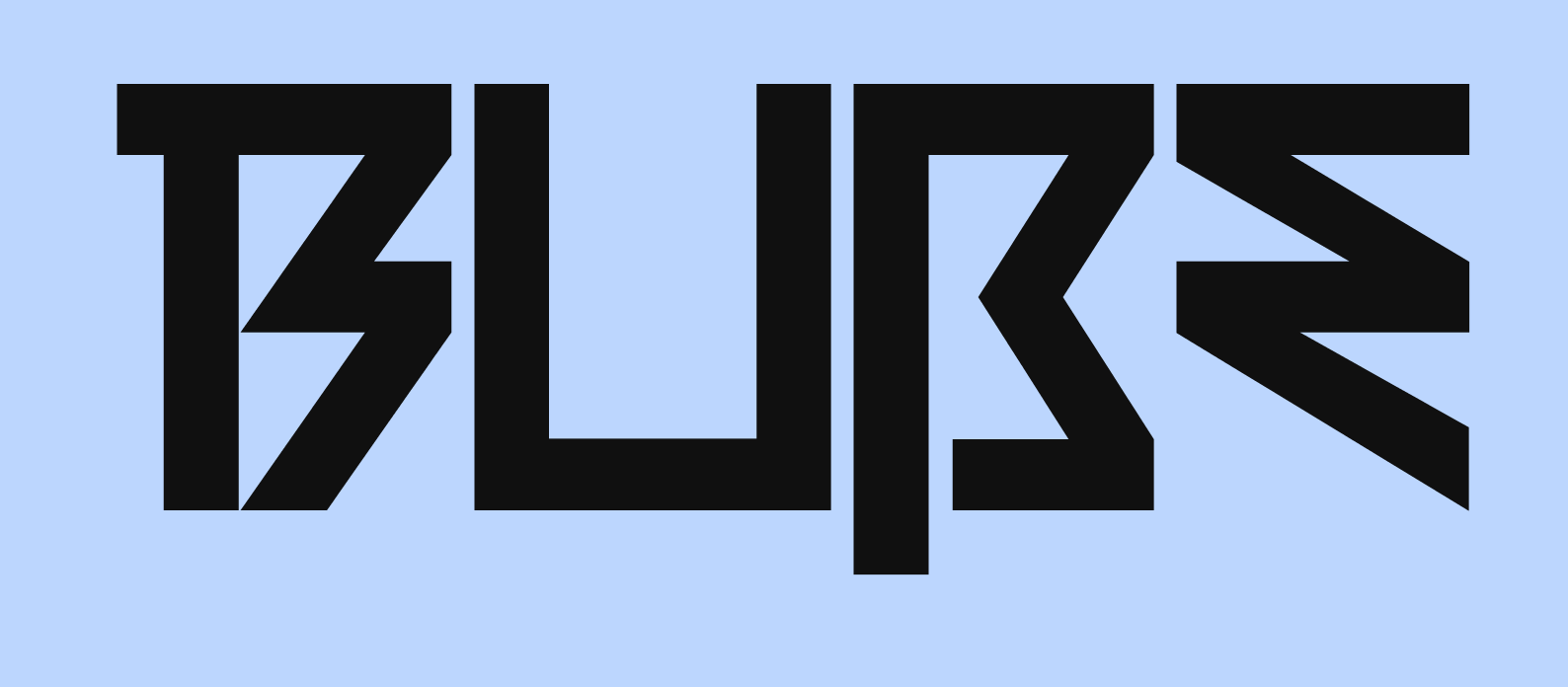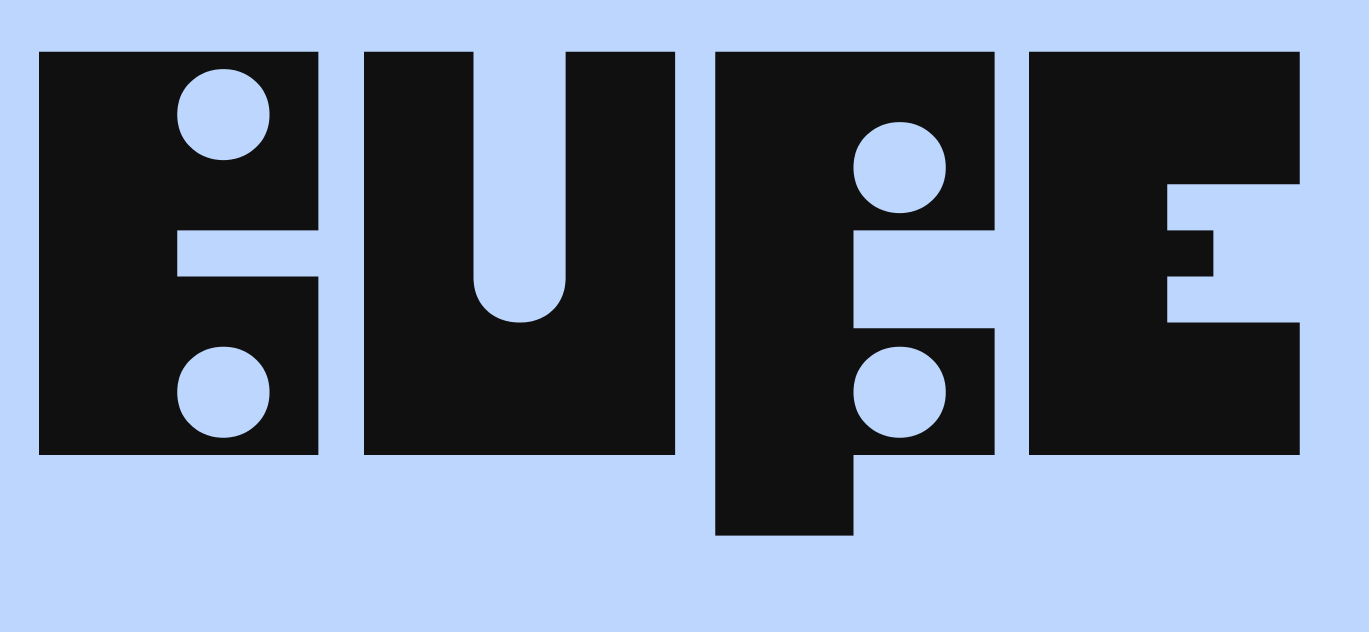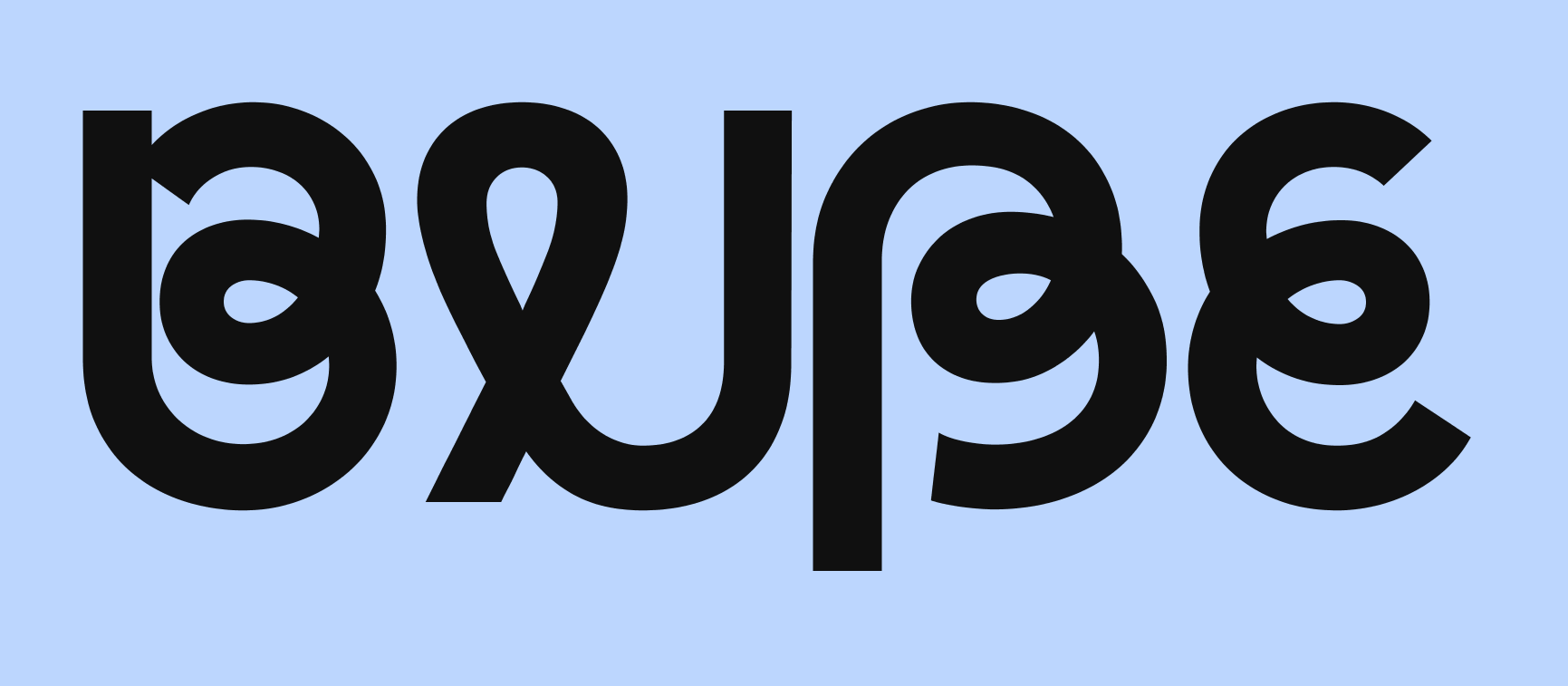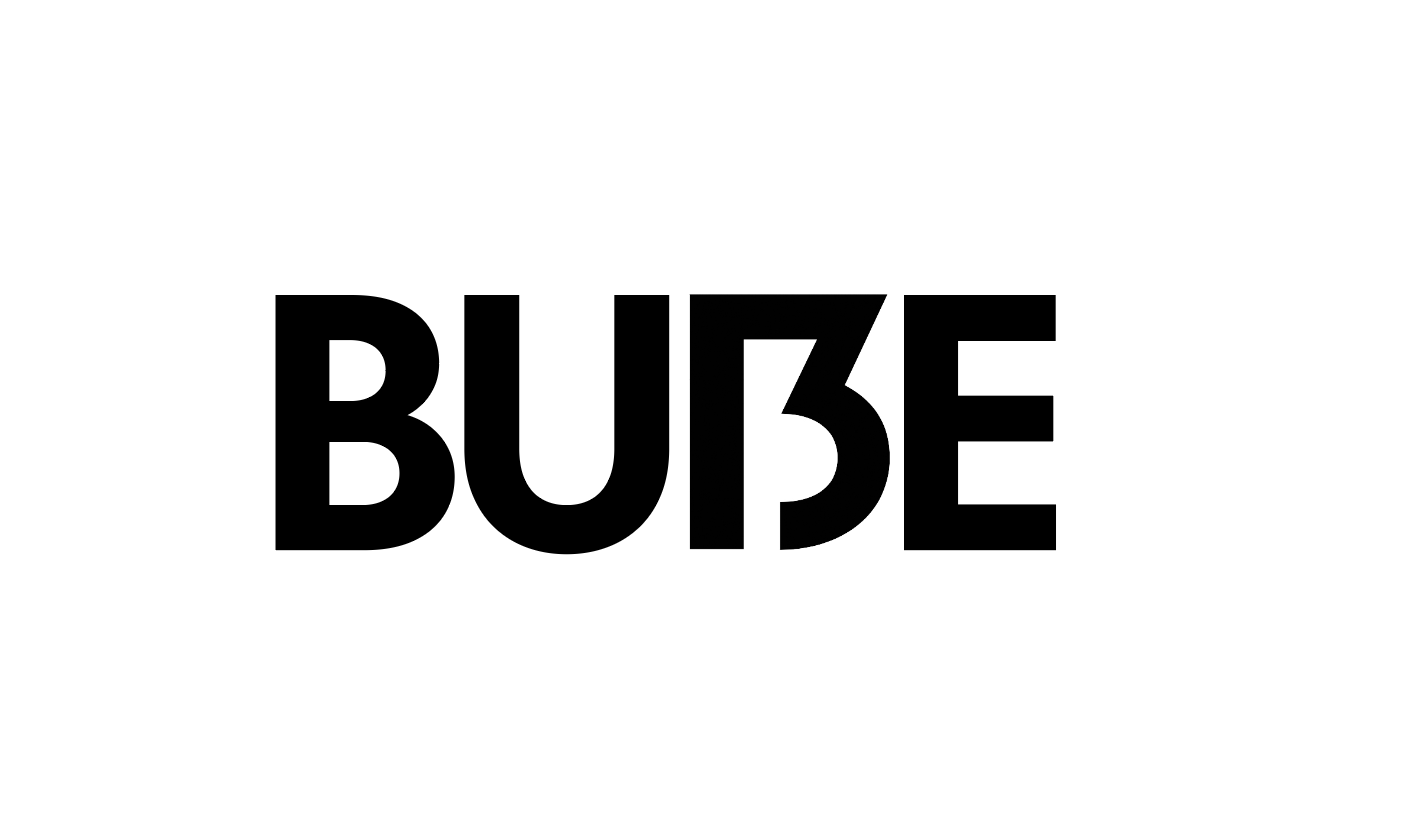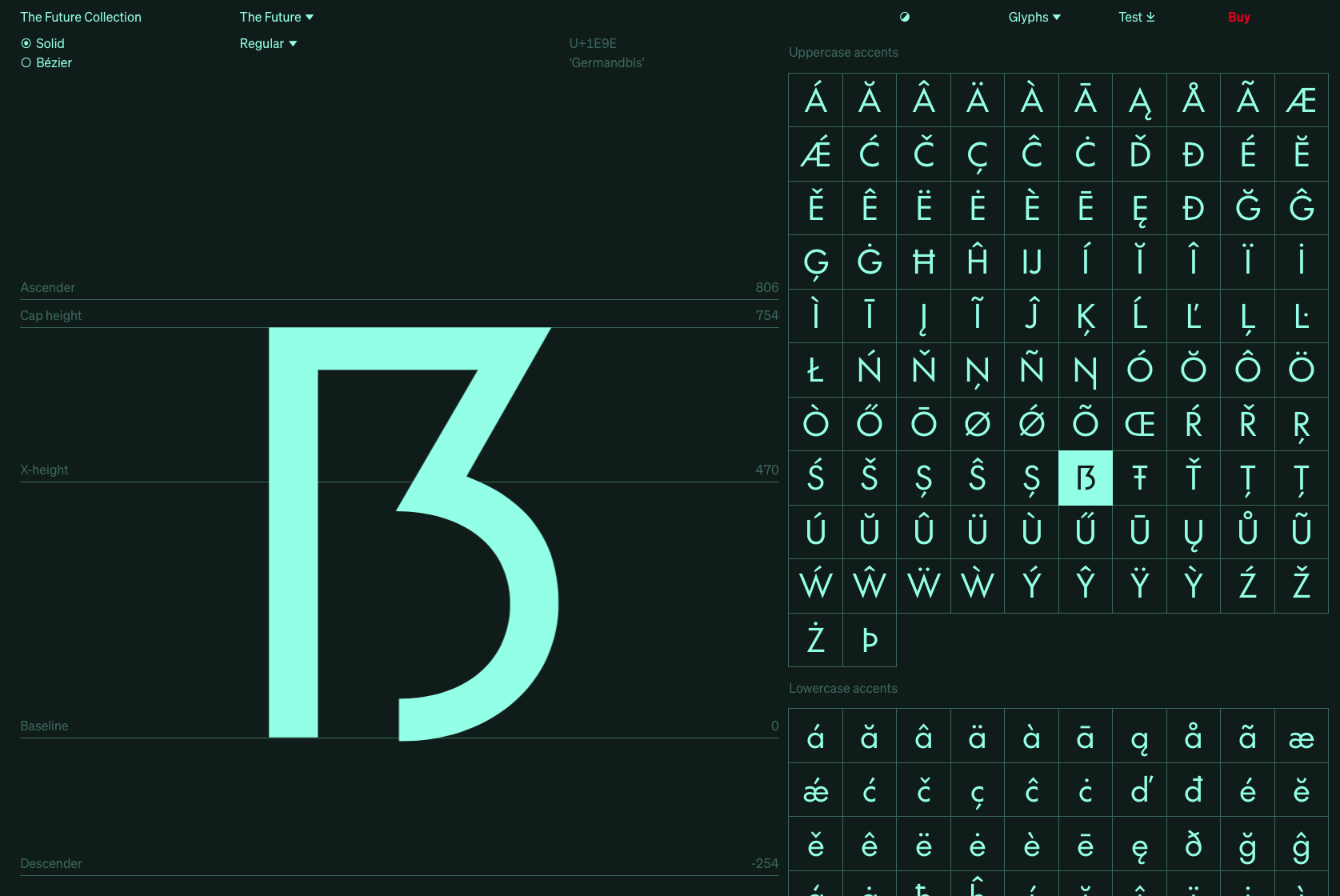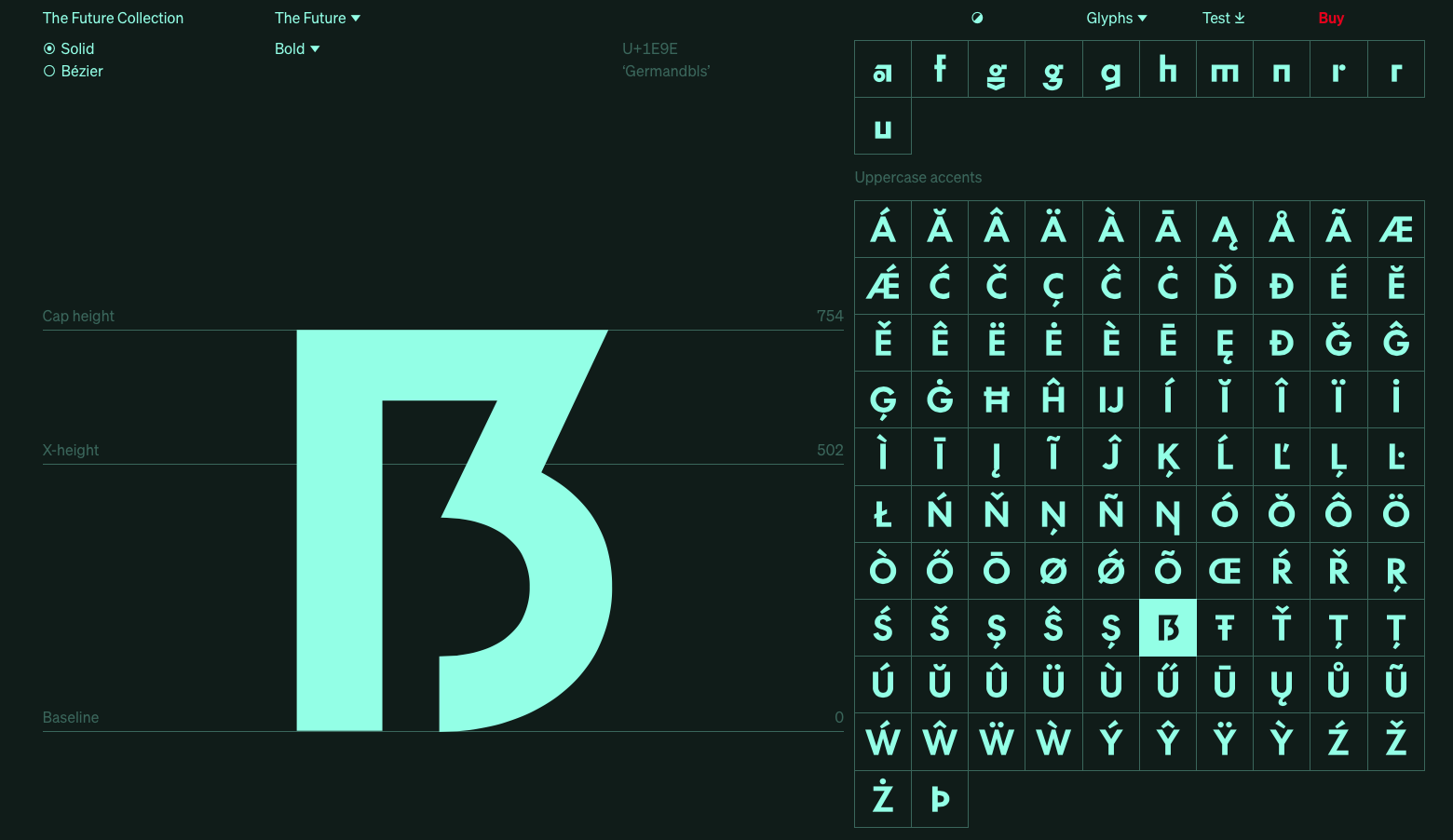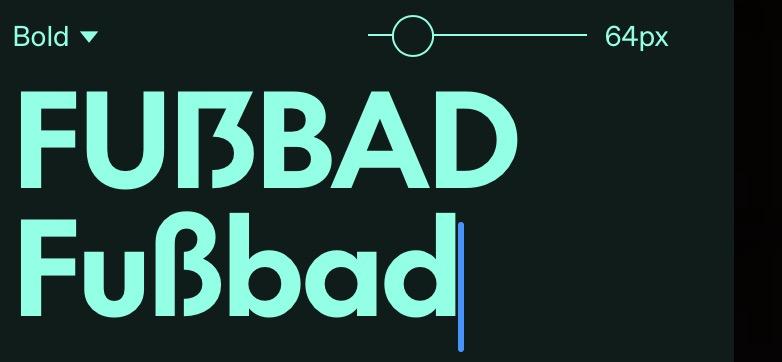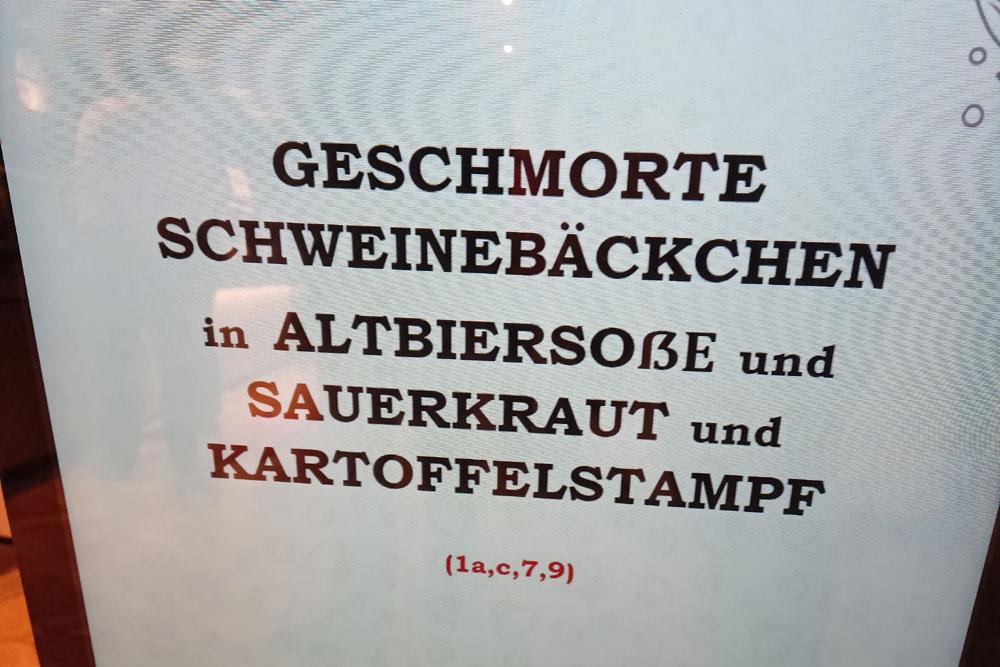
Wenn hier einer eine Einlegesohle braucht ist es die obere Innenform. Viel zu klein im Vergleich zur Unteren.
Aber dann wird sie ja noch kleiner! 😳😜
Ich arbeite mit solchen verspielten Titelsatzschriften ja nie, aber für den geneigten Liebhaber: drei Ausarbeitungen von Radim Pesko.
A) Lÿno Ulys / Lÿno Walt
B) Paabo
Klim Type Foundry: The Future Collection
Leider gibt es auf der Seite der KTF keine Try-Option, dafür aber ein Test-Kit zum freien Download mit allen Schriften (Basisversionen ohne Sonderzeichen). Deshalb habe ich das Eszett kurzerhand selbst in PS freigestellt, um einen Eindruck eingebettet in ein Wort zu vermitteln …
Leider gibt es auf der Seite der KTF keine Try-Option […] Deshalb habe ich das Eszett kurzerhand selbst in PS freigestellt, um einen Eindruck eingebettet in ein Wort zu vermitteln
Die Stilübersicht kann man einfach als Eingabefeld nutzen um so etwas auszuprobieren. Das wird inzwischen bei mehr und mehr Foundry-Websites ermöglicht – einfach per Klick auf den Schriftschnitt probieren.:tuschel:
Die Stilübersicht kann man einfach als Eingabefeld nutzen um so etwas auszuprobieren. (…) einfach per Klick auf den Schriftschnitt probieren.
Doch so einfach. Muss man erst mal draufkommen … War bisher wohl mehr mit schauen als mit klicken beschäftigt. ; )
Täusche ich mich oder hat Söder hier tatsächlich kein Versal-Eszett verwendet? Dann wäre es ja ein böser Verschreiber, weil ansonsten ja ein SS stehen müsste:
Täusche ich mich oder hat Söder hier tatsächlich kein Versal-Eszett verwendet? Dann wäre es aber ein böser Verschreiber, weil ansonsten ja ein SS stehen müsste:
Der Doppelbeitrag war ein Versehen. Eigentlich wollte ich nur das doppelte »ja« ausmerzen.
Empfehlung für nächstes Mal: Eine Fontalternative für die gesamte Gestaltung. [...] 🙈
Uh, und dann noch den Font vom ß weitergezogen aufs folgende E.
Trotz aller Versuche wirken viele Versal-ẞ wie ein Fremdkörper in der Schrift wofür sie gestaltet wurden. Für eine Schrift wie die DIN (statische lineare Serifenlose bzw. Grotesk mit geometrischem Charakter) eignet sich meiner Meinung nach die sogenannte Sulzbacher-Variante am besten. Nicht nur für das kleine ß, auch für das große ẞ. Die FF DIN hat seit 2018 ein Versal-ẞ nach Sulzbacher-Art, es wurde nie reklamiert.
es wurde nie reklamiert.
Dann tue ich dies hiermit mal. Diese Form ist weder vom ß, noch vom B eindeutig zu unterscheiden. In der Tat fügt es sich daher eher der Gewohnheit, aber der Nachteil, keine eigene eindeutige Form zu haben, überwiegt für mich deutlich.
idealerweise sollten Versalien, Kleinbuchstaben, Ziffern usw. gut zu unterscheiden sein. Ich denke, dass sich in der FF DIN ß und ẞ sich besser von einander unterscheiden als 1, I und l in der Gill und als I und l in Akzidenz-Grotesk, Futura, Helvetica, Univers, ITC Avant Garde Gothic und Frutiger. Oder das kleine o und die Mediävalziffer 0 in fast allen Schriften. Egal ob Antiqua oder Grotesk. Wenn einer bei Monotype sich daranmacht und in diesen Schriften, ähnlich bei der Frutiger 1450, das l mit einem ‘DIN-Haken’ versehen wurde, würde das wahrscheinlich (und zurecht) viele Schriftgestalter und Typografen auf die Barrikaden rufen. Gleiches passiert wahrscheinlich auch wenn die Mediäval-Null um Wille der Leserlichkeit standardmäßig mit einem Schrägstrich versehen würde. Es geht bei diesen Schriften nicht nur um Leserlichkeit, aber auch um die Gestaltung. Auch wenn sich a, g und q in der Avant Garde schlecht unterscheiden, die Schrift verkörpert ein Gestaltungsprinzip und ihre hiervon bestimmte Anmutung kommuniziert somit Qualitäten die in der visuelle Kommunikation gut und gerne eingesetzt werden. Deswegen ist meiner Meinung nach gut und richtig nicht nur viele verschiedene Schriften, aber auch eine gewisse Formenvielfalt bei den Buchstaben selbst haben zu können.
Ich würde mich in der Tendenz Ralf anschließen wollen: Im Grunde ist es doch über Jahrzehnte bis zum heutigen Tag einhelliger Konsens, dass das ß unter Versalien nichts zu suchen hat. Insofern bin zumindest ich immer erstmal irritiert, ein »echtes« ẞ zu sehen, dass aber formal nahezu wie ein ß aussieht. Das unterbricht tatsächlich das störungsfreie Leseerlebnis. Bei den von Dir angeführten Beispielen gibt es diese Diskrepanz so nicht.
Nun ja, nur weil Ed Benguiat damals für die ITC Bauhaus so ein blödes B gestaltet hat, kann das doch kein Verbot dafür darstellen, dass man diese Form nicht mehr für ein Versal-ẞ verwenden darf? Da gibt es für andere Buchstaben wahrscheinlich auch eine Menge andere Beispiele von Schriften in der merkwürdige Lösungen gefunden worden sind. Das oben gezeigte B der ITC Bauhaus wäre höchstens ein Problem wenn jemand in einem Satz oder Text andauernd die ITC Bauhaus und die FF DIN durcheinander verwendet. Wenn es davon ein im wirklichen Leben entstandenes Praxisbeispiel gibt, dann gerne her damit ;-)